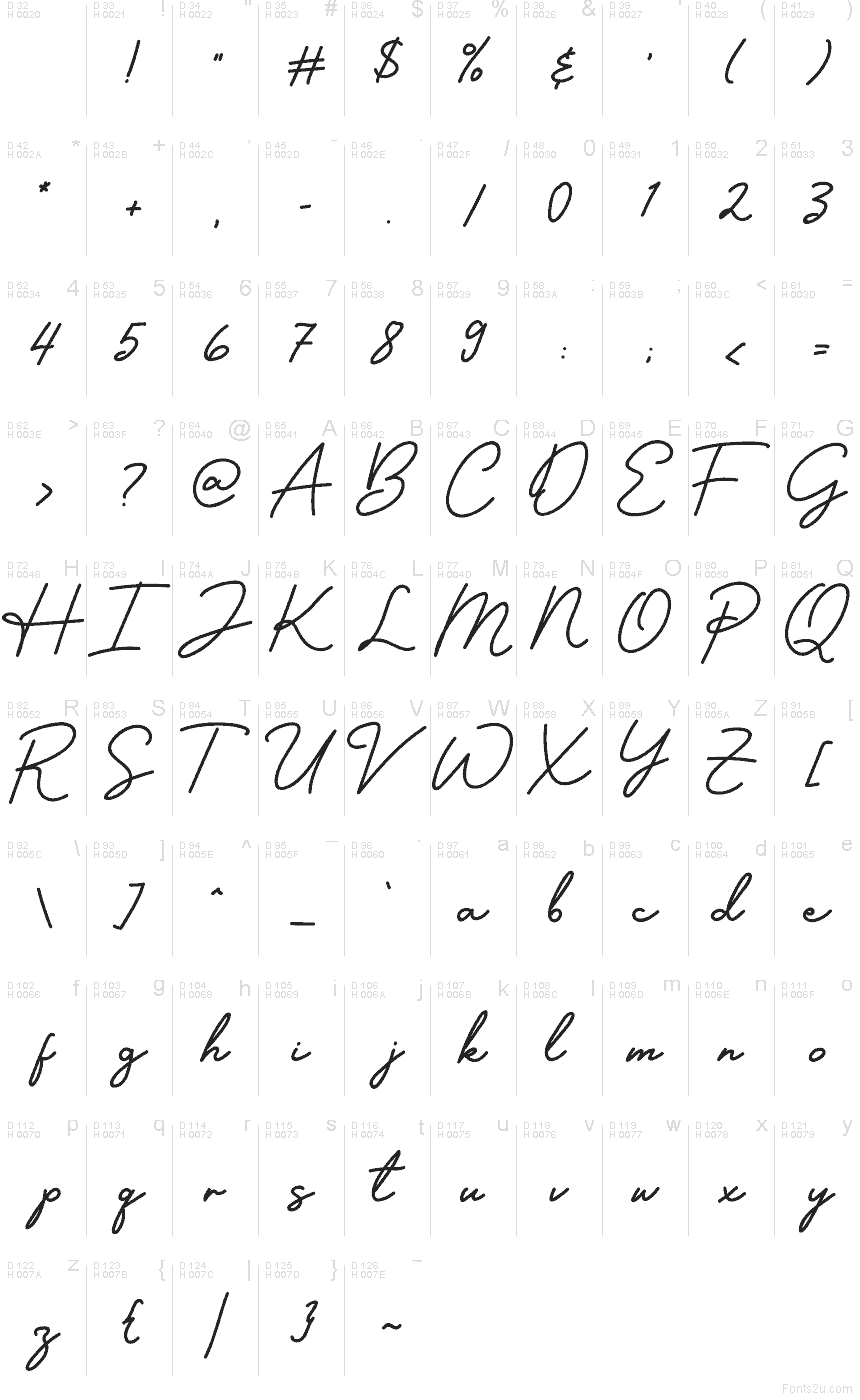
Designer Signature par Graphicfresh Corporation est une police manuscrite gratuite, évoquant la légèreté d’un croquis de mode avec ses mouvements longs et sinueux. Les lettres balayent la ligne d'un geste fluide, mêlant courbes aériennes et quelques accroches plus vives pour un rendu personnel et authentique, plutôt que trop travaillé.
Elle s'intègre naturellement dans le branding, le packaging beauté, les logos de boutiques, les visuels pour réseaux sociaux, la papeterie de mariage ou les titres de magazines, apportant cette touche signée à la main. Utilisez-la pour des noms courts, des titres ou des monogrammes, car ses traits étirés et ses boucles ouvertes donnent à chaque mot l'allure d'une signature spontanée.